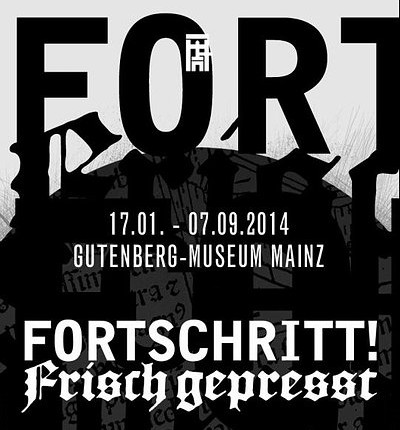
Fortschritt! Frisch gepresst" - Handschriften und frühe Drucke aus dem Gutenberg-Museum Mainz
17. Januar bis 7. September 2014, Gutenberg-Museum
Mit „Fortschritt! Frisch gepresst“ hat das Gutenberg-Museum jetzt wieder eine Wanderausstellung zu seinem „Kernthema“. Das Konzept erlaubt einen unproblematischen, internationalen Verleih der kompletten Ausstellung als Botschafter aus und für Mainz.
„Fortschritt! Frisch gepresst“ konzentriert sich auf die Zeit des Umbruchs zwischen Schreibstube und Offizin: Nachdem mehr als 1.000 Jahre Bücher mit der Hand (ab-)geschrieben worden waren, führte das Aufkommen und Wachsen der Städte zu einer schnell ansteigenden Nachfrage nach Büchern: Seit dem 14. Jahrhundert gab es immer mehr Bürger, die lesen und sich die kostbaren Bücher leisten konnten. Neben der reinen Anzahl waren es auch die Inhalte der Bücher, die neuen Anforderungen gegenüber standen: Bislang gab es kaum volkssprachliche oder unterhaltsame Literatur. Die Inhalte der kostbaren Codices, die bisher zumeist in den klösterlichen Schreibstuben geschrieben wurden, waren dementsprechend christlich geprägt.
Als die Schreibstuben den Bedarf nicht mehr decken konnten, ermöglichte die Erfindung von Johannes Gutenberg, der Buchdruck mit beweglichen Lettern, die ungleich schnellere und ökonomischere Buchherstellung. Damit ließen sich Texte beliebig oft und immer identisch vervielfältigen. Erste Offizinen eröffneten und schufen vollkommen neue Berufsbilder wie Schriftschneider, Schriftgießer und Schriftsetzer, Autor, Drucker, Übersetzer und Verleger. Das bislang zumeist in Klöstern streng gehütete Wissen wurde am Ladentisch verkauft, ein globaler wissenschaftlicher Austausch (auf Latein) wurde möglich, das Zeitungswesen entstand; diese erste Medienrevolution wirkt bis heute.
Anhand originaler Handschriften und Inkunabeln vollzieht „Fortschritt! Frisch gepresst“ die Neuerungen und Probleme nach, die Gutenbergs Erfindung mit sich brachte. Eines wird dabei deutlich: Der Buchdruck ließ das Leben keines Menschen unberührt.